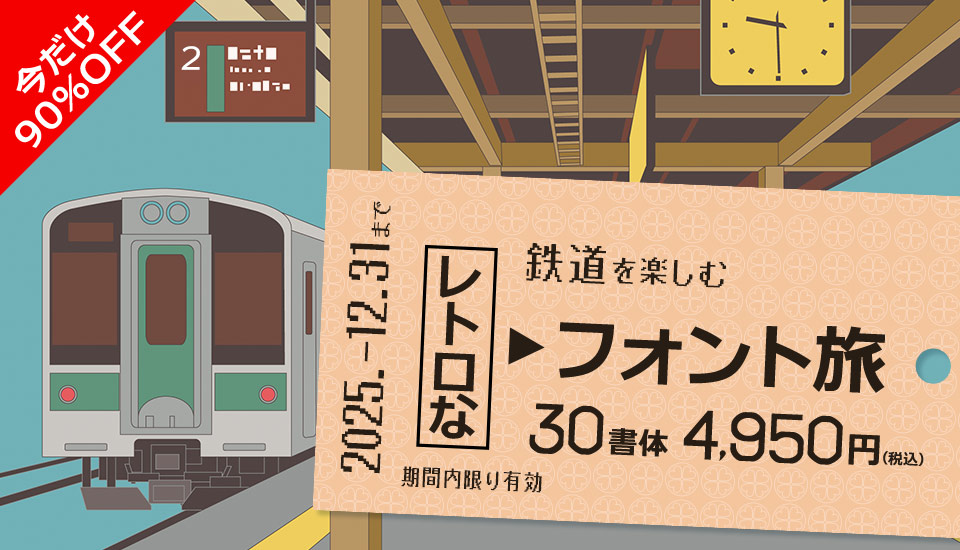
鉄道を楽しむレトロなフォント旅
鉄道周辺の書体を集めた特別セット「鉄道を楽しむレトロなフォント旅」
新幹線の電光掲示板や通勤・通学で見かけるレトロな30書体をまとめた特別セット
使用例
通勤・通学時に使っていた定期券風のデザイン
発車案内板風のデザイン
新幹線早割り
鉄道系の動画作成
収録書体一覧
LED電光掲示板用 AFv1_16dot/AFv2_16dot
LED電光掲示板用に開発された和文です。字形はドットの集合体でカクカクしたデザイン。縦16dotのLED表示器に最適化されています。
v2はv1よりも数字と-+=.の横ドットが太くデザインされています。
電光掲示板みたいなフォント AFSゴシック16●L/16●R
電光掲示板の雰囲気をアウトラインフォントで表現したフォント。街中で見られる電光掲示板のビットマップフォントをドットの形を●で表現した電光掲示板っぽいゴシックフォントです。
16●Rは16●Lよりもドットが大きめにデザインされています。
電光掲示板みたいなフォント AFSゴシック16■R
電光掲示板の雰囲気をアウトラインフォントで表現したフォント。街中で見られる電光掲示板のビットマップフォントをドットの形を■で表現した電光掲示板っぽいゴシックフォントです。
電光掲示板みたいなフォント AFS明朝16●L/16●R
電光掲示板の雰囲気をアウトラインフォントで表現したフォント。街中で見られる電光掲示板のビットマップフォントをドットの形を●で表現した電光掲示板っぽい明朝フォントです。
16●Rは16●Lよりもドットが大きめにデザインされています。
電光掲示板みたいなフォント AFS明朝16■R
電光掲示板の雰囲気をアウトラインフォントで表現したフォント。街中で見られる電光掲示板のビットマップフォントをドットの形を■で表現した電光掲示板っぽい明朝フォントです。
AFSミンノバE
斜体・扁平・長体などの加工フォントシリーズに同梱されていた太字明朝体を単体リリース。見出しはもちろん強調させたい文章に最適な太字明朝体です。
AF-ユニバーサルビュー4書体セット
メイリオの流れを汲むUDフォント、AF-ユニバーサルビューのL・R・DB・Eウェイトをまとめた4書体セット。
テロップ/サムネイル用 AF-UVImpact
AF-ユニバーサルビューシリーズの中でも一番太いインパクトあるユニバーサルフォント。ひらがな字形ついては学参フォントを意識し視認性を強化しました。
AFSデジタル放送TV用ARIB外字付きフォントR
デジタル放送TV用ARIB外字付きフォント。メイリオデザイナー鈴木竹治氏によるドゥRをベースにしニュース報道の本文用に最適化、ARIB STD-B24 6.3版ARIB外字531文字を追加。テロップなどはこの1書体で完結です。
AF-ギザかく20dot
電光掲示板で使われているフォントを模したデザインのビットマップフォント風なTrueTypeフォント。ギザかくシリーズは、四角い形状のドットで字形を構成しました。
定期券日付風 2商品セット
旧国鉄時代の定期券に使われていた日付スタンプを模した数字など、定期券日付風数字フォントの5書体セットです。
AFNewAri Regular
平凡でも可読性に優れ長時間でも疲れない欧文フォント、同人系クリエイター専用としてゲーム、書籍などのソフトウェアにバンドルを許諾した自由度高い欧文フォントです。
AFS復刻欧文フォント AFSFutuM
歴史的に重要且つ著名な欧文を活字印刷から刻まれた雰囲気を残しデジタルフォントへ復刻。1924年パウル・レンナーによるフーツラ・グロテスク(サンセリフ体)の復刻。細めの明るいデザインが特徴。
AFS復刻欧文フォント AFSGillS
1926年ごろエリック・ギルによるギルサンの復刻。見やすく誤読の無い長所を持ち、Mの浅い切れ込み、眼鏡型の小文字のg、R・Q・Jの テールが特徴。
復刻欧文 AFSNeuSansR
AFSNeuSansのウエイトをLクラスから少し太くしRに改版しました。何処にでも違和感なく使える便利な本文用書体です。